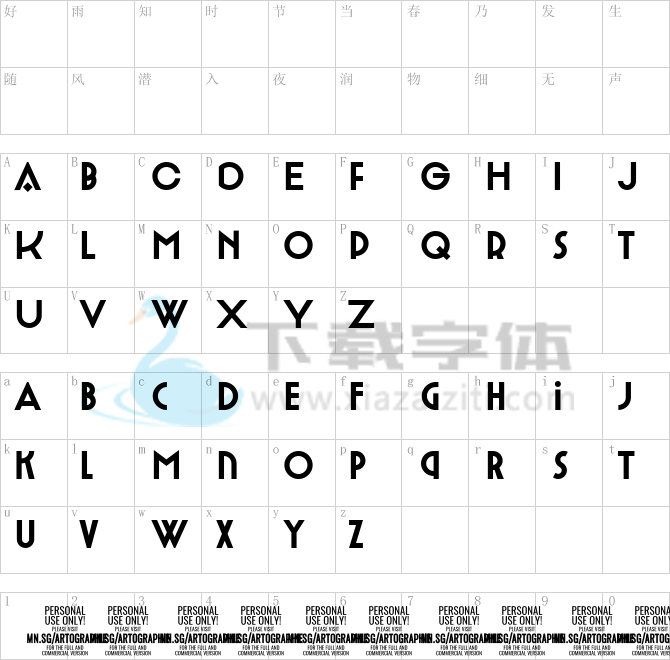
Artographie Black.ttf字体下载,这款字体结构工整、笔画清晰,兼顾美观与易读性,适用于标题、正文、海报、包装、LOGO 等多种场景。字形优雅稳定,风格百搭耐看,适配日常排版与创意设计,让文字呈现更舒适、更具质感。Artographie Black.ttf字体下载一笔一画,皆是细节,以均衡的比例、流畅的线条打造舒适视觉体验,字形端正大气,风格简约现代。无论是商业设计、品牌宣传还是日常排版,都能轻松驾驭,让文字更有格调与力量。Artographie Black.ttf字体下载字体下载。